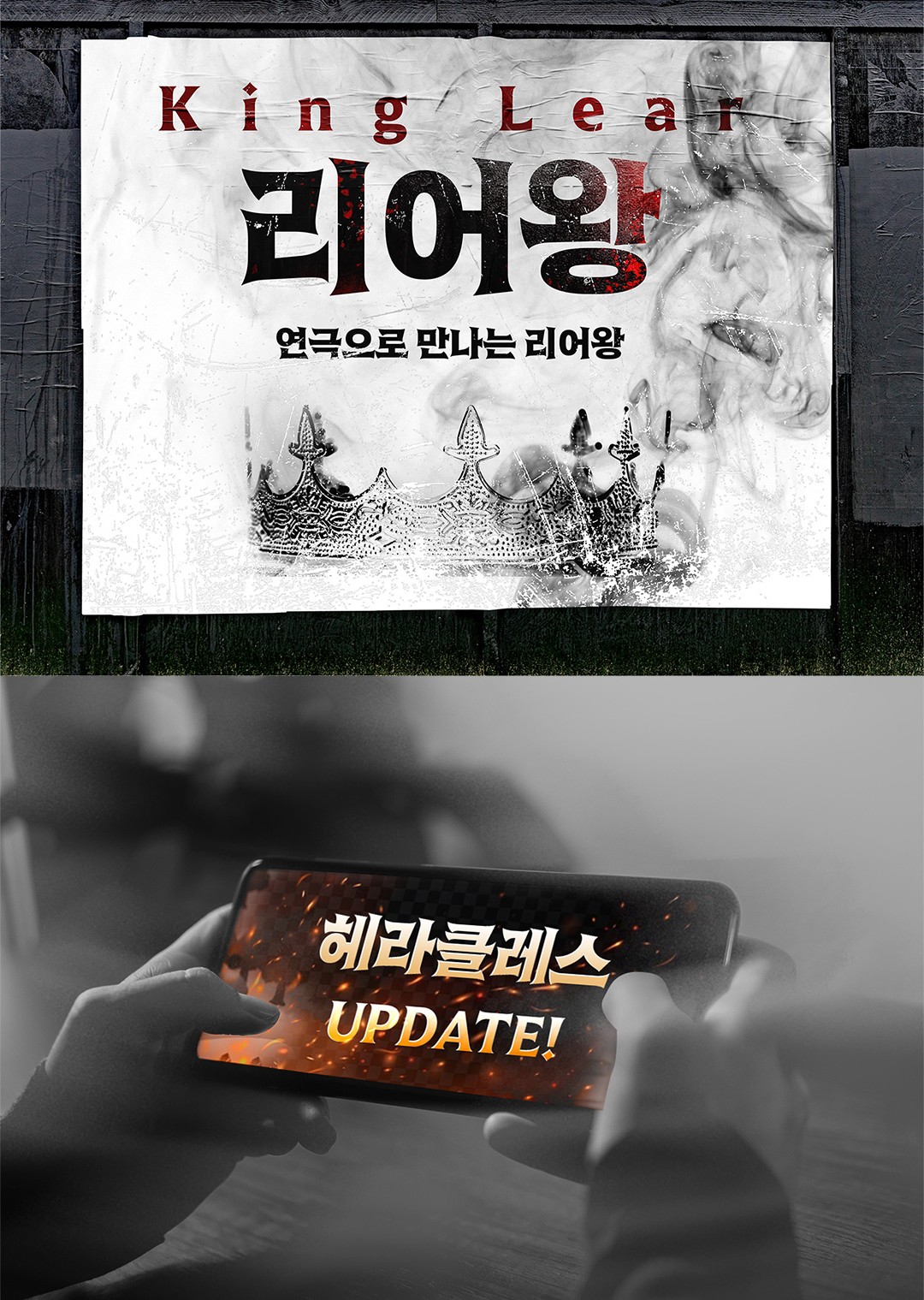
Rix글라디우스는 고대 로마 비문에 새겨진 글자에서 영감을 받아 제작한 강한 인상의 서체입니다.
시원하게 뻗은 두꺼운 뼈대와 넓게 벌어지는 획의 끝단, 날카로운 세리프가 특징입니다.
시선을 사로잡고 강렬한 메시지를 전달하여 광고, 게임, 도서 등에 제목용 폰트로 활용하기 좋습니다.